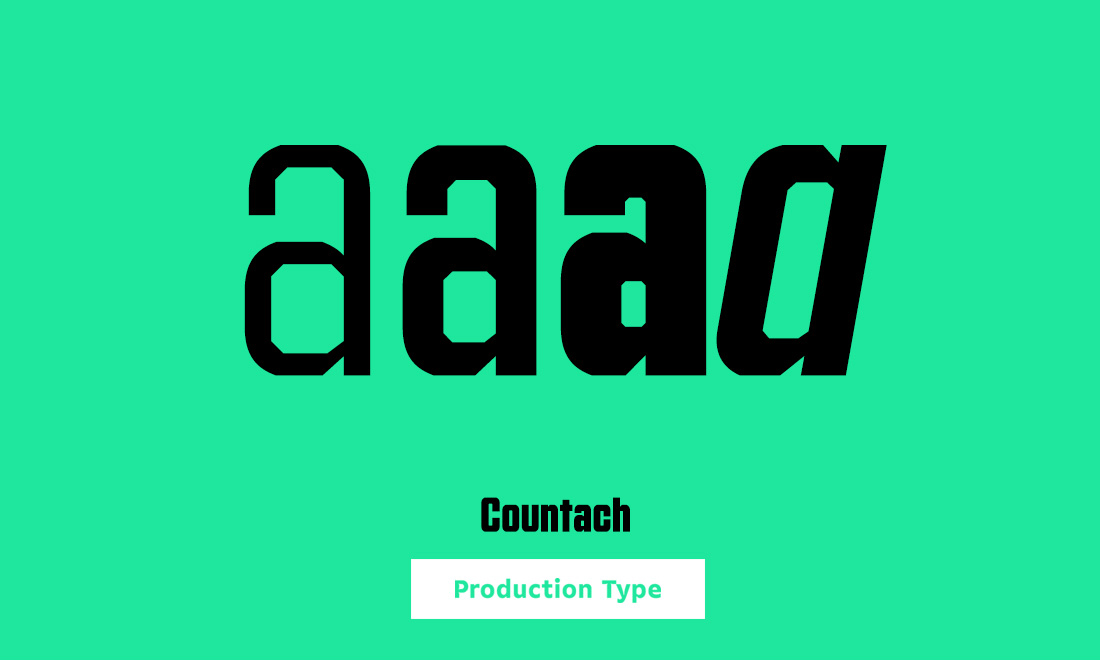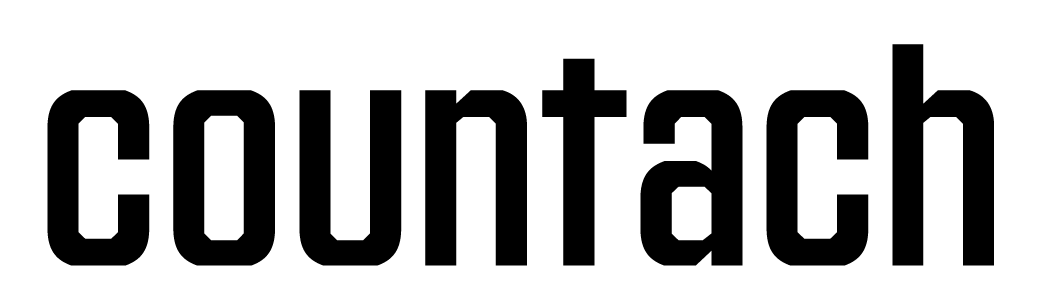
- 자동차 게임을 위해 탄생한 폰트인 Countach는 사용자 인터페이스에서 시각적 아이덴티티에 이르기까지 진정한 자동차 문화를 어필하고, 크고 작은 크기로 다양한 정보를 전달하기 위해 사용된다.
강한 선, 뾰족한 각, 속도를 전달하는 이탤릭체 등 이 폰트가 갖고 있는 정교함과 디테일은 단순히 견고하고 모듈화 되어 있다는 것 이상으로 Countach가 뛰어난 폰트라는 것을 말해주고 있다.